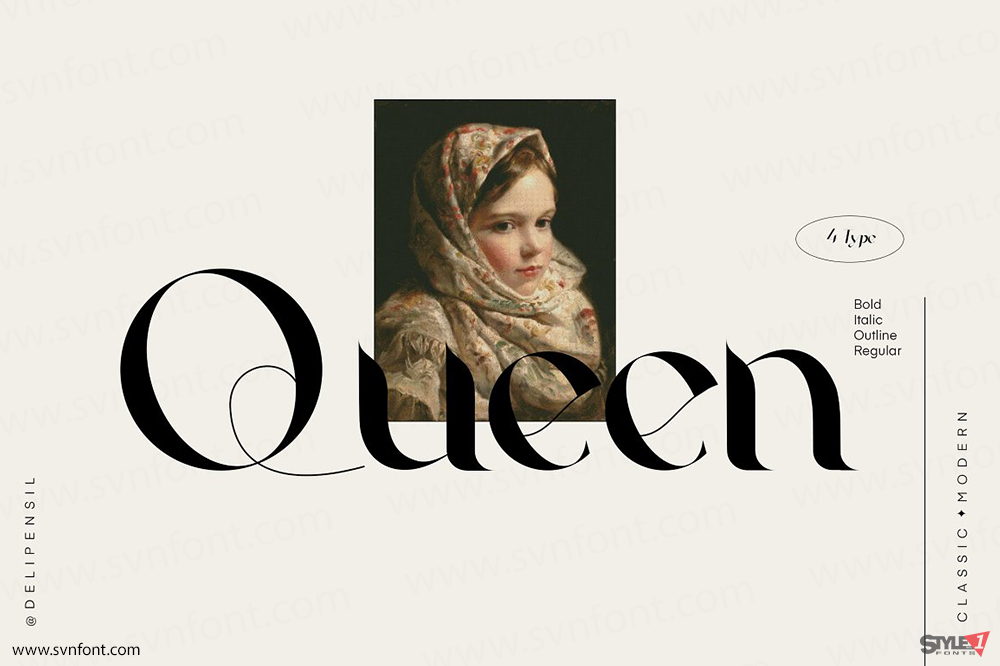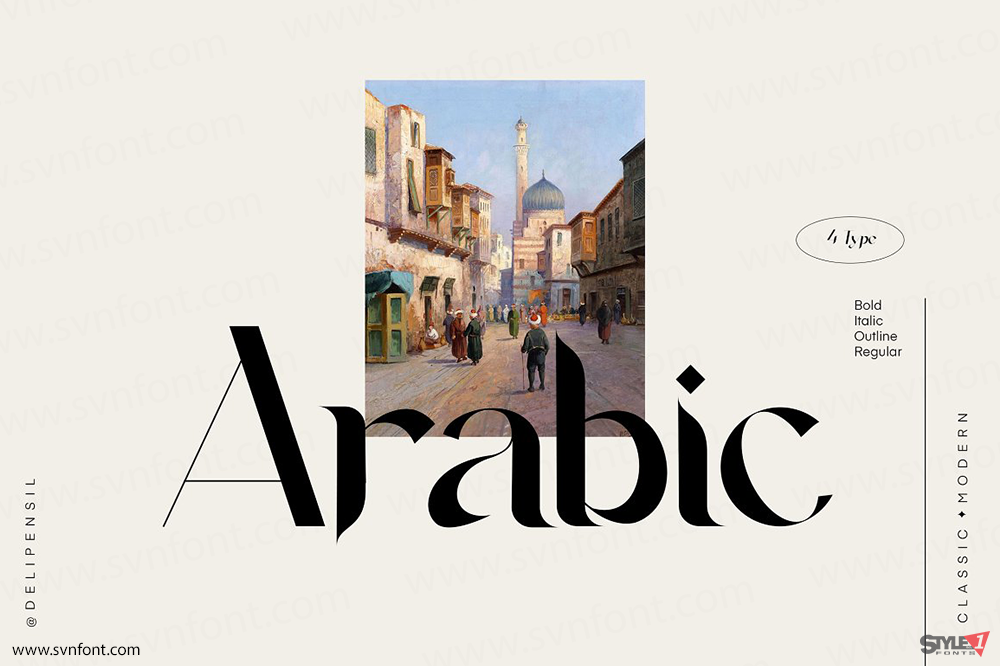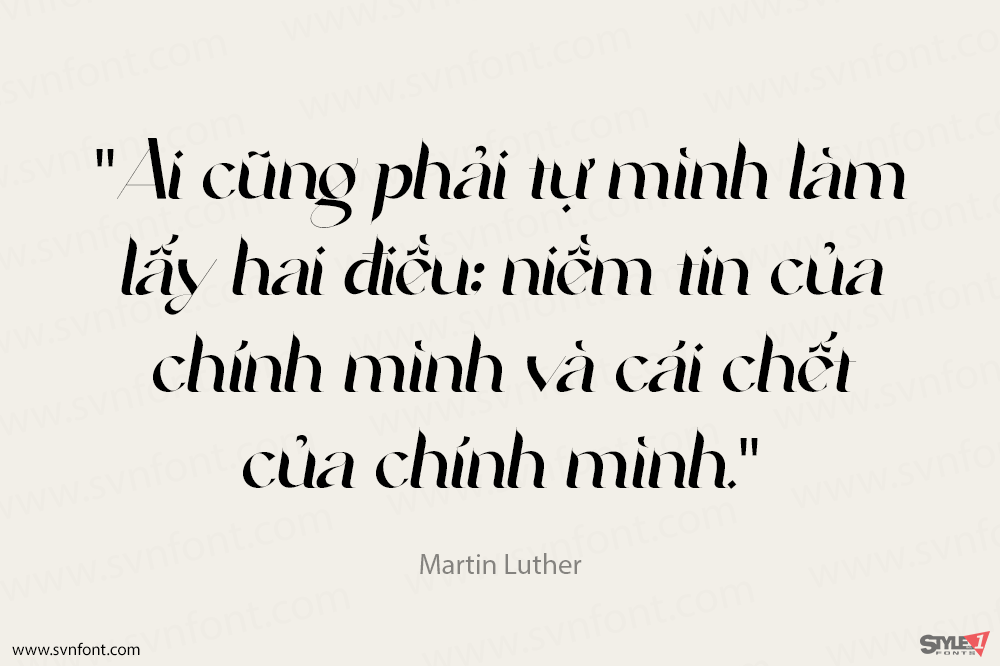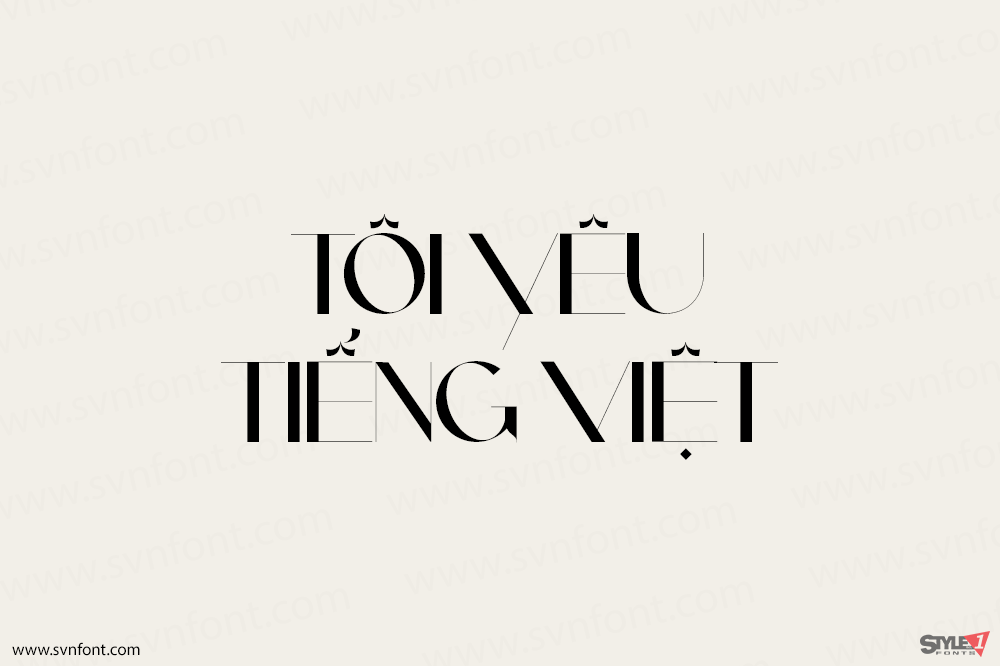
Giới thiệu Agoka — một typeface serif hiện đại mang vẻ đẹp cổ điển. Agoka sở hữu nét thanh lịch, tinh tế, sạch sẽ và đầy chủ ý, hội tụ trong một bộ chữ duy nhất. Font đặc biệt phù hợp cho các dự án mang tính thẩm mỹ cao như logo, tiêu đề, bìa sách, tạp chí, website và nhiều ứng dụng sáng tạo khác.